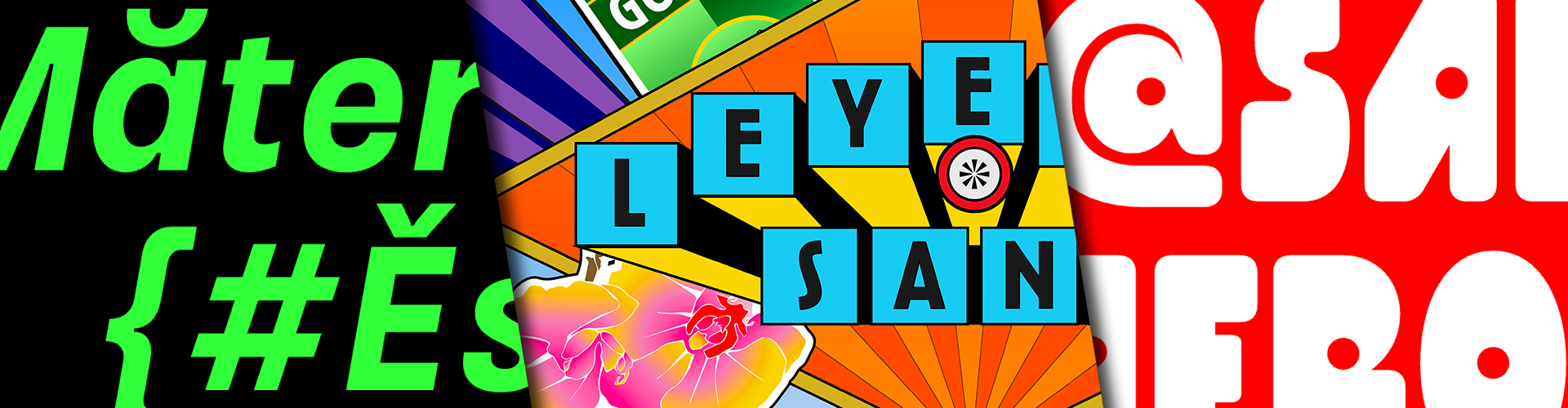
Tipografía, el arte invisible explicado por Bastarda
Crear una tipografía es un acto de precisión y creatividad, una mezcla de arte y matemática que define cómo leemos el mundo. ¿Cómo se hace? La autora conversó con Bastarda Type para entender mejor, de la mano de seis de las fuentes que han creado, cómo es ese proceso que comienza en la mano del tipógrafo y termina impresa en los ojos de quien la lee.
No hay, quizá, forma de arte más ignorada e inadvertida que el diseño tipográfico. Literalmente frente a nuestras narices, omnipresente. Aún así, rara vez o casi nunca nos preguntamos por las letras que sostienen las palabras —¿quién las creó?, ¿en qué están inspiradas?—, y sin embargo, su diseño define nuestra experiencia. Una mala tipografía nos hace tropezar o perdernos del camino. Una buena, nos conduce sin que lo notemos, nos lleva de la mano por lo escrito.
Una tipografía es un sistema de escritura. Es el diseño que hace que una ‘a’ en Arial no sea la misma ‘a’ en Comic Sans. Diferente a la rotulación o el lettering, la creación de todo el abecedario, con sus signos y símbolos, y el funcionamiento armónico de cada uno de esos elementos, es lo que convierte a un grupo de letras en una tipografía.
El origen de las tipografías se suele situar con la invención misma de la imprenta —aunque se sabe que antes de Gutenberg hubo tipos móviles— y desde entonces se han creado distintas tipografías. Tan arraigado está este arte a su origen que la terminología para hablar del diseño tipográfico sigue ligada a esa era pre-digital: los estudios que hacen tipografías se conocen como fundidoras, por la fundición de los plomos para hacer los tipos.
Con la llegada de las computadoras se dio el verdadero boom y el momento en que Colombia comenzó a entrar al juego del ABC. ¿Pero para qué seguir creando tipografías si hay millones que funcionan? “Es como la personalidad de las personas”, dice Sebastián Castellanos de la Hoz, cofundador de Bastarda Type, una fundidora bogotana. Y habrá tantas tipografías como personalidades.
Una ‘E’ no puede modificarse porque ya tiene una estructura para que se entienda que es una ‘E’”, agrega Jason Guzmán, también cofundador de Bastarda, pero esa estructura se viste de manera que se vea diferente a las que ya existen o sirva para lo que va a ser usada; puedes ponerla de corbata o de sudadera”.
Las tipografías en sí mismas comunican, transmiten un mensaje. Y no basta con decir algo, hay que vestirlo con la voz adecuada.
¿Qué soy y qué quiero ser?
En el comienzo existe el concepto. Sabor, modernidad, innovación, elegancia. Son conceptos que pueden transmitirse a una tipografía y que definen si su forma deberá ser más cuadrada, más redonda, más delgada; si los trazos son más gruesos, más finos o más raros. Así se empieza a diseñar.
Luego viene la definición técnica: ¿para qué se va a usar? ¿Dónde se ve esa tipografía cuando sea grande: en un aviso, un libro, una revista científica o de moda, una aplicación para celular? Su función define su forma. La tipografía es el cuerpo de las palabras, su textura, su temperatura. La voz del mundo. Y esa voz debe poder entenderse.
Una vez definidas las ideas y funciones, la mano toma su lugar. Con un dibujo. Ahí es donde empieza el verdadero trabajo que hace que el diseño tipográfico sea más que arte y se convierta en arquitectura. “Es un dibujo vectorial. Se dibuja letra por letra y se va creando un sistema. Y en ese proceso de dibujo uno hace pruebas de impresión, dialoga entre varias opciones de ‘a’, cuál se siente mejor, cuál se lee mejor a determinado puntaje, cuál es la más llamativa”, aclara Sebastián. La estructura va tomando las formas que habitamos con la mirada.
Para ser tipógrafo hay que tener tanta pericia como paciencia. Estar dispuesto a abrir un mismo archivo una y otra vez por meses. Un proyecto básico de tipografía puede durar tres meses y constar de 200 a 250 dibujos, porque no solo debe cubrir las 27 letras del abecedario; también debe incluir signos de puntuación, de marcación, monetarios y de otras lenguas. Entre más universal quiera ser una tipografía, más elementos requerirá.
Todo este tiempo y trabajo para hacer una letra que no interfiera en la lectura, sino que guíe de manera natural y fluida, o que diga sin decir: “Ven. Léeme”.
Letras, son y sabor
El diseño tipográfico bebe de otras artes. Izzy Sanabria, el director de arte de Fania Records, fue la inspiración para crear Salsa BT, la tipografía más famosa, más completa y más descargada de bastardatype.com.
Jason y Sebastián tomaron la portada del álbum de la Fania All Stars grabado en vivo en el Cheetah Club de Nueva York, y desarrollaron una tipografía. “El objetivo era que se viera muy salsero, que tuviera sabor”, explica Jason, que al ver las letras los pies reaccionaran y se movieran al compás de la clave.
Salsa BT es una tipografía de títulos y por eso no tiene minúsculas. Existen dos vertientes: las fuentes para texto o las fuentes display; para titular. “Queríamos que llamara mucho la atención y por eso sus formas tenían que ser raras, tomando lo que Izzy Sanabria hizo en ese par de álbumes”, Cheetah 1 y 2, añade Jason. Las formas cuadradas y gordas se fueron integrando hasta lograr una apariencia muy latinoamericana.